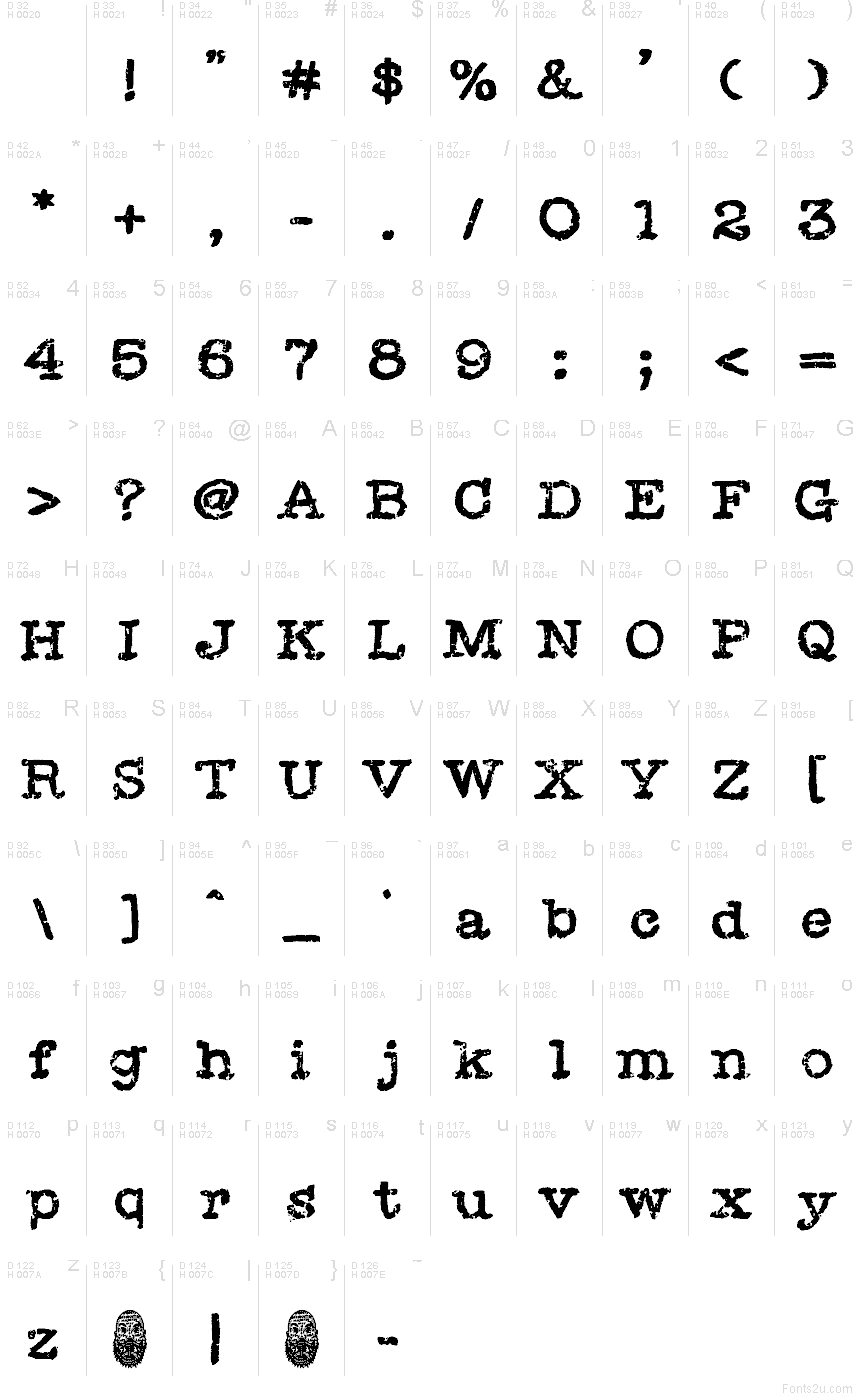
Painful Typewriter
Painful Typewriter de Woodcutter Manero es una tipografía display gratuita con un aspecto erosionado que recuerda a la marca contundente y desgastada de una cinta de máquina de escribir sobre papel irregular. Las letras parecen desgastadas en los bordes y con zonas emborronadas, lo que da a todo el diseño un ritmo analógico y bruto que se siente más auténtico que nostálgico.
Es una fuente gratuita ideal para pósteres de estilo pulp, portadas de fanzines, títulos de películas, flyers, packaging y portadas de libros que busquen una estética de impresión desgastada. También funciona muy bien en titulares cortos y citas, donde su textura irregular hace gran parte del trabajo, aportando una sensación de tensión y artesanía incluso a las palabras más simples.